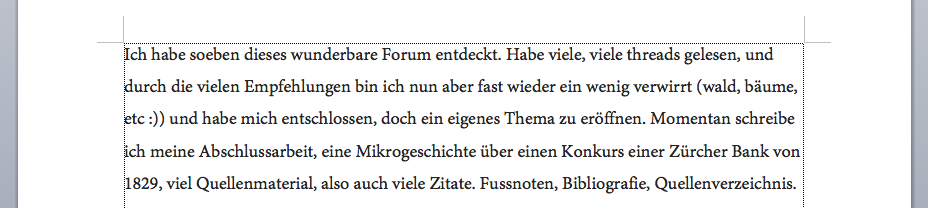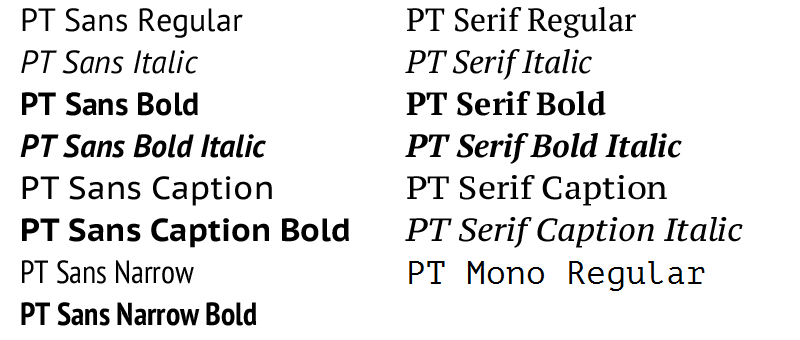
Schrift für Lizentiats-/Masterarbeit in Wirtschaftsgeschichte
Ich habe soeben dieses wunderbare Forum entdeckt. Habe viele, viele threads gelesen, und durch die vielen Empfehlungen bin ich nun aber fast wieder ein wenig verwirrt (wald, bäume, etc :)) und habe mich entschlossen, doch ein eigenes Thema zu eröffnen. Momentan schreibe ich meine Abschlussarbeit, eine Mikrogeschichte über einen Konkurs einer Zürcher Bank von 1829, viel Quellenmaterial, also auch viele Zitate. Fussnoten, Bibliografie, Quellenverzeichnis.
Formale Vorgaben sind folgende:
Formal sollte eine am Lehrstuhl verfasste Liz-Arbeit, bei einer Schriftgrösse von 12Pkt., 1,5zeilig und standardisierten Seitenrändern, 80-100 Seiten umfassen (ab 120 Seiten muss eine Sondererlaubnis eingeholt werden).
Abgeben muss/kann ich zwei verschiedene Versionen:
Insgesamt müssen am Ende drei Exemplare der Lizentiatsarbeit eingereicht werden. Die beiden Dokumentationsexemplare sollten einseitig bedruckt und mit festem Einband versehen werden. Dasjenige, welches Prof. XXX erhält, sollte, leichtgewichtig und handlich gestaltet, beidseitig bedruckt, mit einer Ringspirale zusammengehalten und mit einem weniger festen Einband versehen werden
Dazu will ich noch 5-10 Exemplare mehr drucken, für Familie, Freundin etc. Werde ca. 100 Seiten Lauftext haben plus nochmals ca. 80 Quelleneditionen. Diese Vorgaben sind dehnbar, aber ich kann sie nicht völlig über Bord kippen. Ich hätte aber gerne weniger Zeilenabstand, unterschiedlich breite Seitenränder und will unbedingt zweiseitig drucken.
Nun meine Fragen:
- Habt ihr mir vielleicht eine Empfehlung für passende Schriften (gratis, am liebsten Opensource)
- Was würde ihr gegenüber den Vorgaben am ehesten ändern?
- Wie könnte ich die Quellenedition (2. Teil, 80+ S.) gestalten, damit ich möglichst viel Text auf wenig Raum bringe?
Nur ganz auf die Schnelle (weil es schon spät ist) zwei erste spontane Gedanken, die mir beim Lesen Deines Textes durch den Kopf gingen:
Erstens, am Zeilenabstand würde ich zuletzt sparen. Ein ausreichend oder auch gerne etwas großzügiger bemessener Zeilenabstand erleichtert das Lesen einer solchen Arbeit. Und in der Regel will man dem Professor das Lesen ja nicht schwerer machen als nötig, eher im Gegenteil. Ich würde also vom vorgegebenen Zeilenabstand nicht ohne Not abweichen.
Zweitens: Wenn es um die Schriftwahl geht, würde ich Dir eine Schriftfamilie empfehlen, die über eine Serif, eine Sans Serif und idealerweise auch einen schmalen Schriftschnitt verfügt. Letzteren könntest Du dann wunderbar für Deine Quellenangaben einsetzen und damit einiges an Platz sparen.
Erstens, am Zeilenabstand würde ich zuletzt sparen. Ein ausreichend oder auch gerne etwas großzügiger bemessener Zeilenabstand erleichtert das Lesen einer solchen Arbeit. Und in der Regel will man dem Professor das Lesen ja nicht schwerer machen als nötig, eher im Gegenteil. Ich würde also vom vorgegebenen Zeilenabstand nicht ohne Not abweichen.
Das sehe ich auch so. In allergrößter Not maximal von 1,5- auf 1,2-zeilig.
Zweitens: Wenn es um die Schriftwahl geht, würde ich Dir eine Schriftfamilie empfehlen, die über eine Serif, eine Sans Serif und idealerweise auch einen schmalen Schriftschnitt verfügt. Letzteren könntest Du dann wunderbar für Deine Quellenangaben einsetzen und damit einiges an Platz sparen.
Und weil Du da eine Gratis-Schrift suchst, würde ich Dir zur PT-Familie von ParaType raten. Ein Ausnahmetalent unter den Freefonts, welches alle berechtigten Anforderungen von Kathrin sehr gut abdeckt. (Die Caption- und Mono-Schnitte ignoriere einfach, das wird sonst für diese Zwecke zu kompliziert.)
Frohes Schaffen und gut’ Nacht :-)
Falls formal möglich und für dich umsetzbar, würde ich die Quellenangaben zweispaltig setzen. Meistens hast du da ja kurze Absätze, und die produzieren bei einspaltigem Satz viele halbgefüllte Zeilen, was viel Platz verschwendet.
Und die Caption-Schnitte der PT Sans/Serif kannst du für kleine Fußnoten verwenden. :-P
Mein kurzer Gedanke zur Nacht:
Ich lese die formalen Vorgaben nur als Maßstab, um die Länge der Arbeit korrekt einschätzen zu können (vergleichbar mit den "Normseiten", die Übersetzer zugrunde legen), nicht als typografische Empfehlung. Aus meiner Leseerfahrung vieler, vieler geistes- und sozialwissenschaftlicher Texte in Times New Roman 12 pt, mit 1,5fachem Zeilenabstand und "Standard"-Rändern würde ich sagen: Diese Vorgaben sind eine Zumutung bei längeren Texten. Ich würde deshalb eher raten, 10 pt mit angemessenem Zeilenabstand und sehr großzügigen Rändern, um eine optimale Zeilenlänge zu garantieren.
Welcher Art sind denn die Quellen im Anhang? Eher längere Texte? Eher Tabellen und Statistiken? Oder tatsächlich nur die Literaturangaben zum Text?
Solche Vorgaben sind wirklich eine Zumutung.
Du verwendest vermutlich DIN-A4-Papier. Mit den oftmals benutzten schmalen Rändern (um 2,5 cm) sind dort die Zeilen bei einspaltigem Satz viel zu lang. (Eine Faustregel für die Zeilenlänge ist, daß eine Zeile im Durchschnitt nicht mehr als 12 Wörter enthalten sollte.) Bei den viel zu langen Zeilen braucht man nun wiederum einen sehr großen Zeilenabstand, sonst verrutscht man beim Lesen ständig in der Zeile. Bei einer sinnvollen Zeilenlänge kann man den in der Regel viel zu großen Zeilenabstand von 1,5 Zeilen deutlich auf normale Werte verringern. (Die Angabe „1,5-zeilig“ ist allerdings nicht genormt und ergibt unterschiedliche Abstände je nach Programm, Schrift, Druckertreiber ua.)
Und gerade noch eine Frage: Gibt es irgendwie Grundsätze, wo man Kopfzeilen (mit Kapitelüberschrift) und Fusszeilen (Seitenzahlen) platziert? Kopfzeilen inner- oder ausserhalb des Satzspiegels?
Es kommt darauf an, ob die Kopf-/Fußzeilen in der Regel so voll sind, daß sie als ganze Zeilen wirken: Enthalten sie meistens nur ganz wenig Text, beispielsweise ein kurzes Wort und eine Seitenzahl, dann gehören sie nicht zum Satzspiegel; bei mehr Text schon.